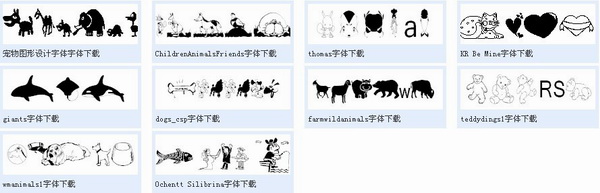
動(dòng)物字體打包是多款藝術(shù)英文字體,以動(dòng)物為原型字體可愛美觀,小編為大家?guī)?lái)了多款比較常用的動(dòng)物字體,喜歡的朋友歡迎來(lái)綠色資源網(wǎng)下載使!
本款動(dòng)物字體打包共有10款,分別是寵物圖形設(shè)計(jì)字體、ChildrenAnimalsFriends字體、thomas字體、KR Be Mine字體、giants字體、dogs_csp字體、farmwildanimals字體、teddydings1字體、wmanimals1字體、Ochentt Silibrina字體。